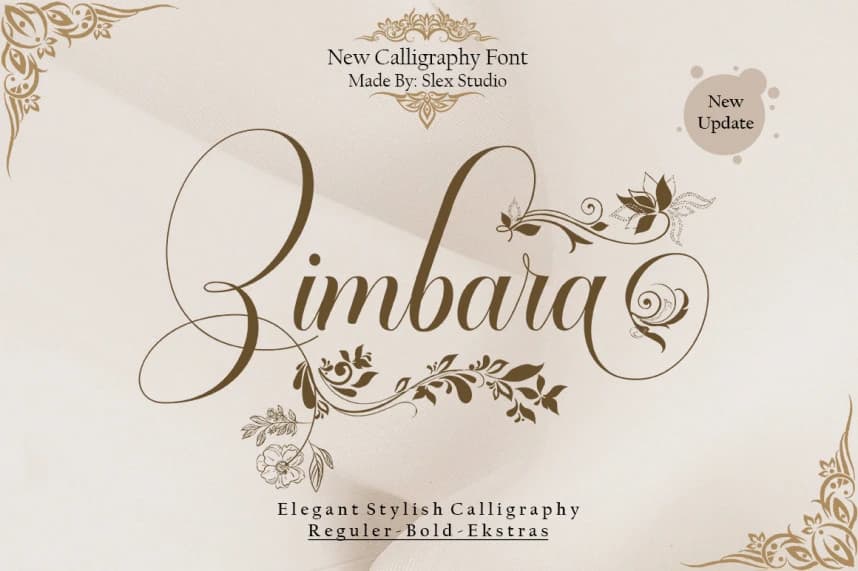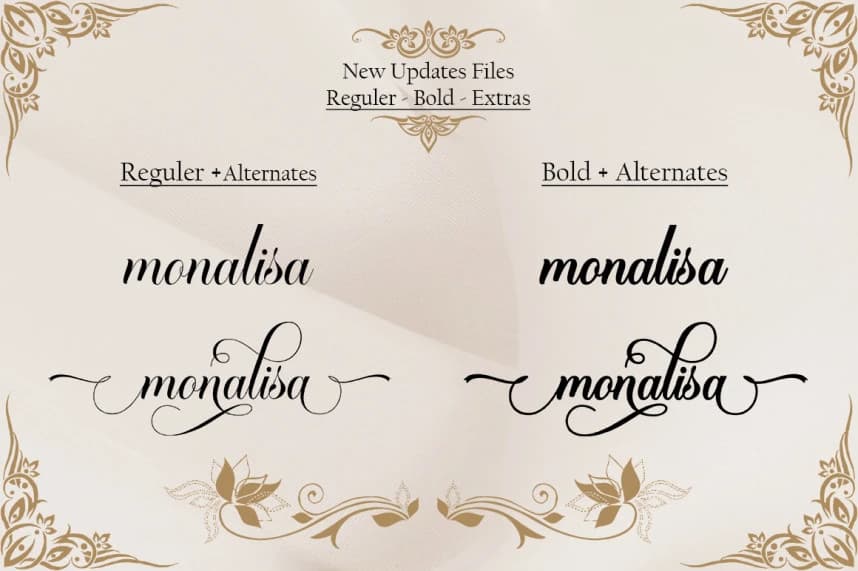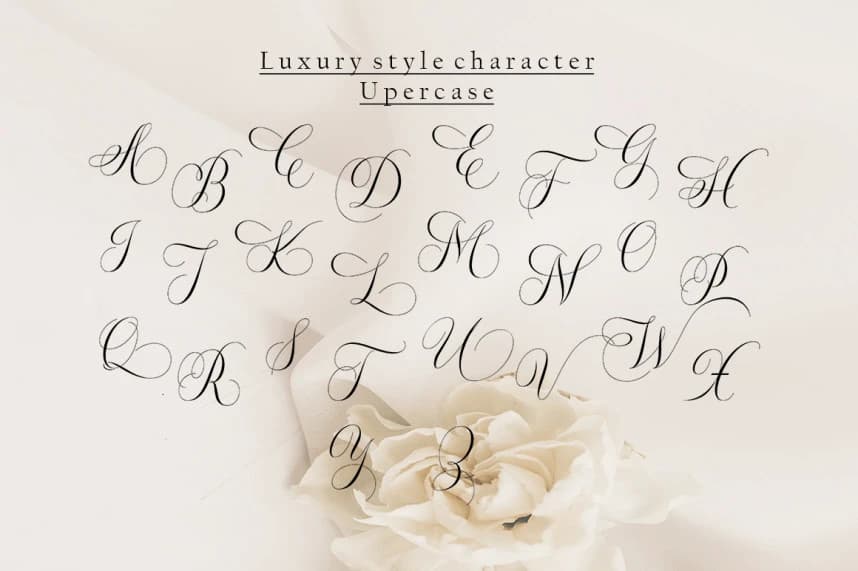
Zimbara Script Font
Zimbara script font, Now plus Bold font ve beautiful Extras, klasik bir stile ve zarafetin bir dokunuşuna sahip olan, antik el yazmalarının kaleminden ilham alınmıştır. Birlikte uyum içinde çalışacak şekilde özenle tasarlandı; bu da onu düğün tanıtım materyalleri için son derece uygun kılıyor.
Zimbara script font Now plus Bold font ve güzel Extras, klasik bir stil ve zerafet dokunuşuyla, antik el yazmalarının yazı stilinden ilham alınmıştır. Birlikte uyum içinde çalışacak şekilde özenle tasarlandı ve bu da onu düğün medyası için çok uygun kılıyor.
Zimbara Script